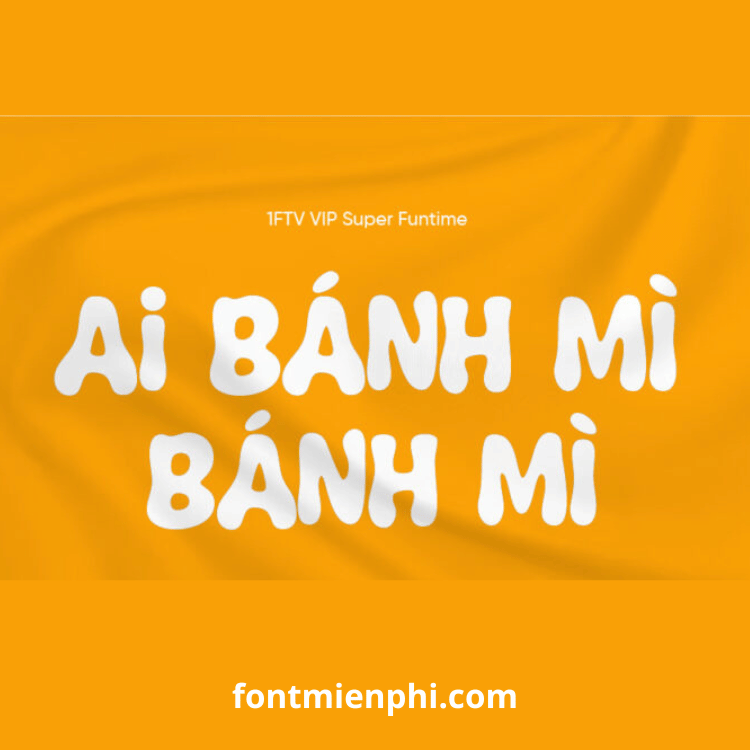
Font Việt hóa 1FTV VIP Super Funtime
Mô tả chi tiết Font Việt hóa “1FTV VIP Super Funtime”
1. Giới thiệu:
“1FTV VIP Super Funtime” là một bộ font Việt hóa độc đáo, được thiết kế với phong cách vui nhộn, sáng tạo, phù hợp cho các dự án đồ họa, game, poster, hoặc thiết kế quảng cáo. Font có nét chữ đậm, bo tròn và nhiều hiệu ứng bắt mắt, mang lại cảm giác năng động và thú vị.
2. Đặc điểm nổi bật:
- Phong cách: Chữ viết tươi vui, phù hợp với thiết kế trẻ trung, giải trí, game hoặc sự kiện.
- Hỗ trợ Tiếng Việt: Đầy đủ dấu và ký tự Unicode, tương thích với mọi phần mềm soạn thảo và thiết kế.
- Nét chữ độc đáo: Có thể kèm hiệu ứng bóng, viền, hoặc gradient tùy chỉnh.
- Đa dạng ký tự: Bao gồm chữ hoa, chữ thường, số, ký tự đặc biệt và biểu tượng.
3. Ứng dụng:
- Thiết kế game, áp phích, banner.
- Làm video YouTube, TikTok, content giải trí.
- In ấn sản phẩm thời trang, phụ kiện.